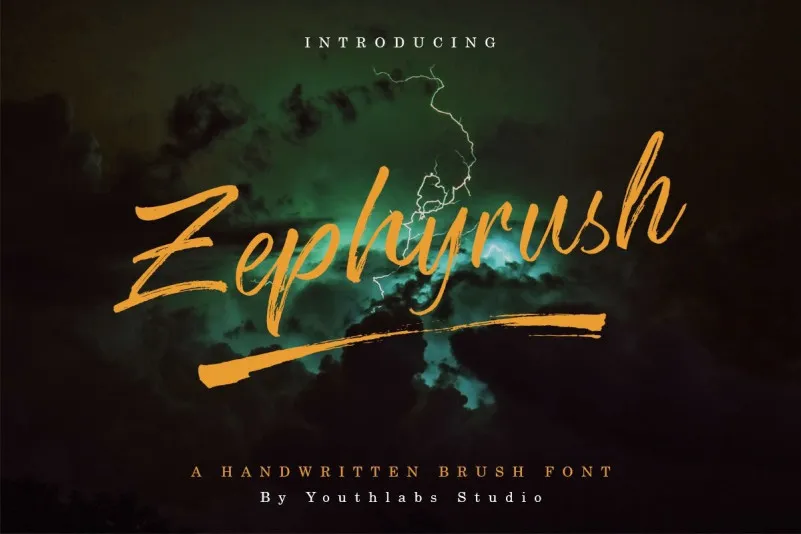
Zephyrush Brush Font – Fonte Grátis
Zephyrush Brush Font
Zephyrush Brush Font é uma fonte script que traz a autenticidade de uma caligrafia manuscrita, elaborada com paixão por Youthlabs Studio. Esta fonte casualmente escrita usa um pen desbotado, criando texturas e fluidez únicas. Ela é perfeita para os projetos variados que exigem um toque autêntico de caligrafia manual. Pode ser usada em fotografias, marcas d’água, posts nas redes sociais, anúncios, logotipos e identidade visual, convites, designs de produtos, etiquetas, material de estação (como fita adesiva ou cartão-postais), arranjos de casamento e embalagens. Além disso, Zephyrush Brush Font também se destaca para eventos especiais e qualquer outra ocasião em que uma caligrafia manuscrita seja desejada.